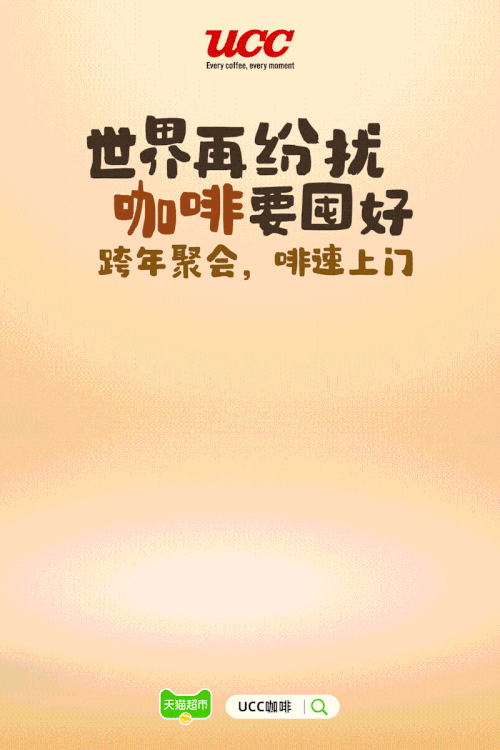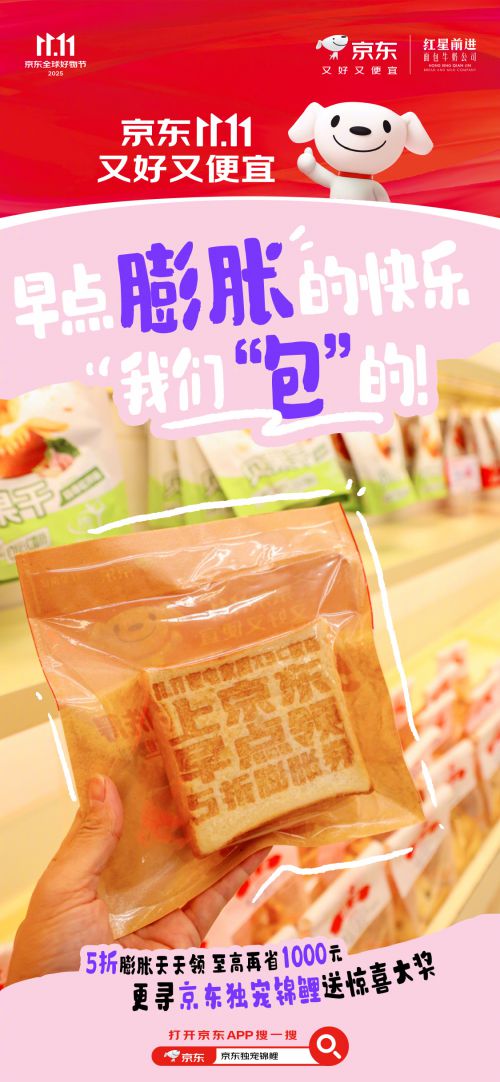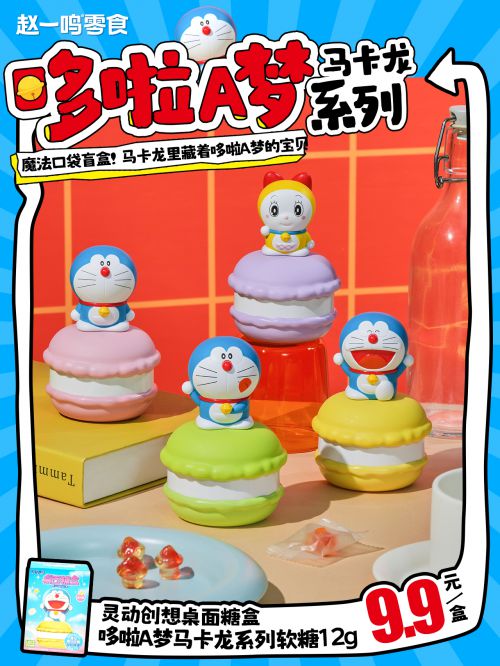
点字蜡笔是点字库推出的一款创意字体,融合卡通、可爱、手写风与趣味性设计,专为传递童真与活力而生。字体支持简体中文与繁体中文常规字符集,适配多场景文字排版需求,是儿童向、亲子类设计项目的理想选择。 点字蜡笔字形偏扁宽,中宫宽博,重心居中,整体呈现舒展大气的视觉效果。这种结构设计既保留了手写字体的随性,又通过宽博中宫增强了文字的可读性,让信息传递更清晰。 点字蜡笔笔型融入圆润装饰元素,模拟真实蜡笔涂抹的质感——粗而均匀的笔画搭配圆头收尾,细节处可见手写的自然痕迹:笔画间巧妙断开的处理,既还原了蜡笔书写时的“不完美”趣味,又为字体注入灵动与稚气,仿佛孩童用蜡笔随心涂画的天真作品。 无论是儿童读物内文、玩具包装设计,还是节日海报、亲子活动宣传物料,点字蜡笔都能以其独特的蜡笔肌理与童话色彩,快速唤醒受众的情感共鸣。作为会员商用字体,点字蜡笔兼顾设计美感与商业价值,让创意项目在传递可爱氛围的同时,轻松实现合规商用。